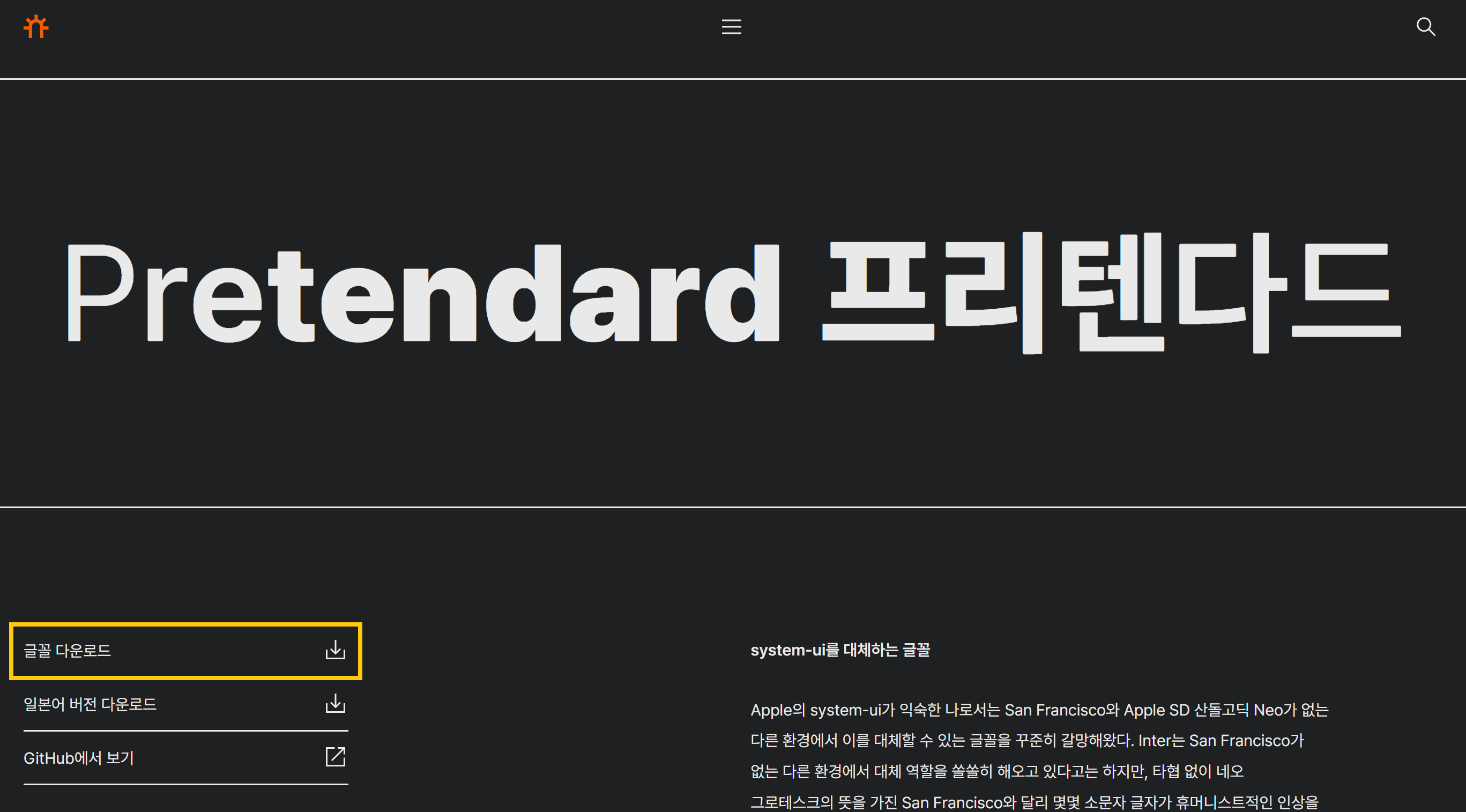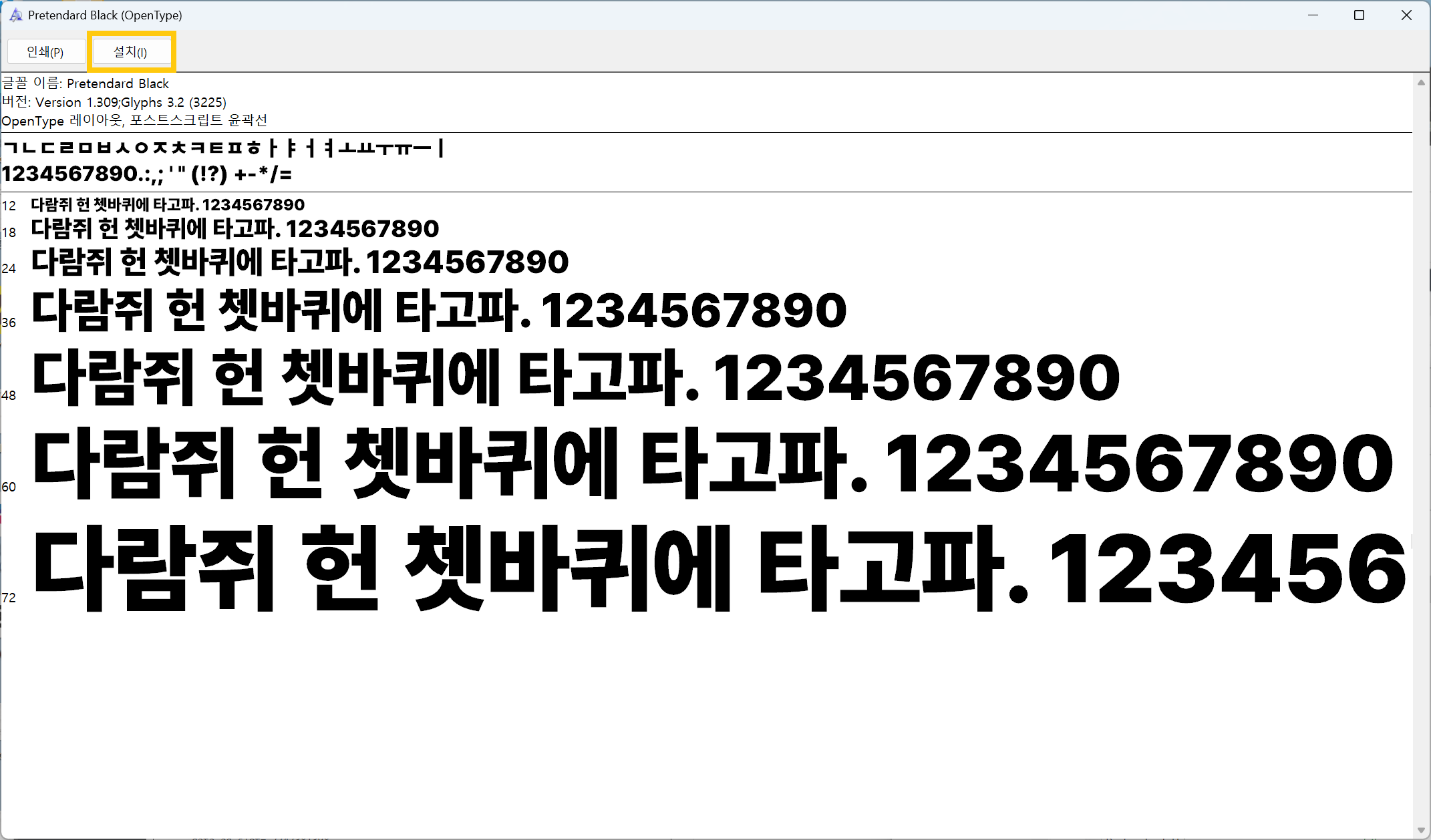
오늘은 현대적인 디자인과 깔끔하고 심플한 프리텐다드 폰트에 대해 알아보려고 합니다. 프리텐다드 폰트는 웹사이트, 인쇄물 등 여러 곳에서 적용하여 기본 글꼴로 사용할 수가 있습니다.
프리텐다드 폰트는 고딕체와 비슷한 느낌이 있어 기독성이 좋아 발표자료를 만들 때 저도 많이 사용하고 있습니다. 기독성이 좋아 디자이너분들도 많이 사용하는 글꼴이라고 합니다. 다양한 폰트 중 디자인 면, 기독성 면도 잡고있는 프리텐다드 폰트 다운로드 방법과 설치 방법에 대해 알아보도록 하겠습니다.
오늘은 프리텐다드 폰트 설치하는 방법에 대해 알아보았습니다. 프리텐다드 폰트가 한가지가 아니고 굵기 마다 조금씩 다른 매력을 주는 듯합니다.
프리텐다드는 글자 간격이 읽기 편하게 되어있어 보기도 편한 것이 좋은 장점인 듯합니다. 저작권없이 무료로 웹사이트, 인쇄물과 같은 다양한 디자인 제작에 활용할 수 있고 상업적으로도 사용이 가능하니 너무 좋은 것 같습니다.